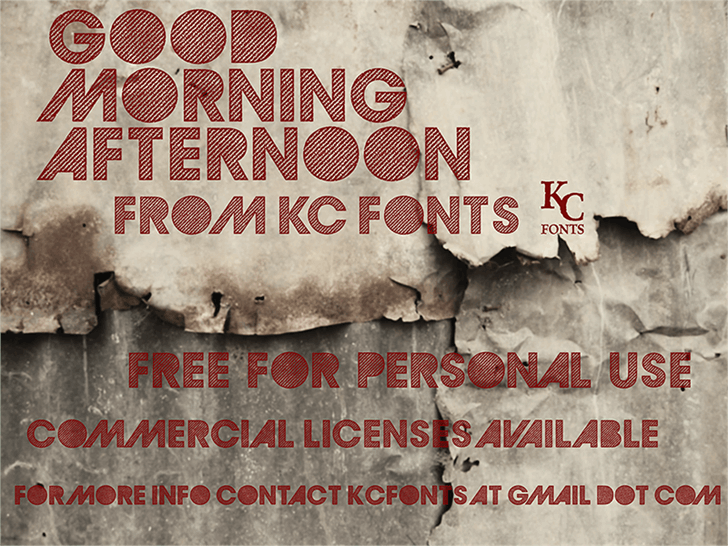
A fonte “GoodMorningAfternoon” é uma seleção de letras com efeitos destacados, perfeitamente adequada para ambientes digitais vivos e coloridos. Desenvolvida pelo designer Hamilton, essa fonte oferece um toque vibrante e dinâmico ideal para aplicações visuais que valorizam a interação visual. Com suas formas fluidas e cores alegres, ela se destaca como uma opção perfeita para projetos pessoais ou iniciantes no design gráfico. Não importa o formato da mensagem ou o ambiente digital em que você estiver trabalhando, essa fonte é ideal para introduzir um ar de descontração e criatividade sem comprometer a legibilidade crucial. Seja para criações digitais de blogs pessoais, posts nas redes sociais ou até mesmo aplicativos de mensagens, “GoodMorningAfternoon” oferece uma escolha divertida que complementa perfeitamente qualquer projeto visual. Para obter mais informações sobre seu uso comercial ou se você estiver em dúvida, não hesite em entrar em contato com a equipe do designer.